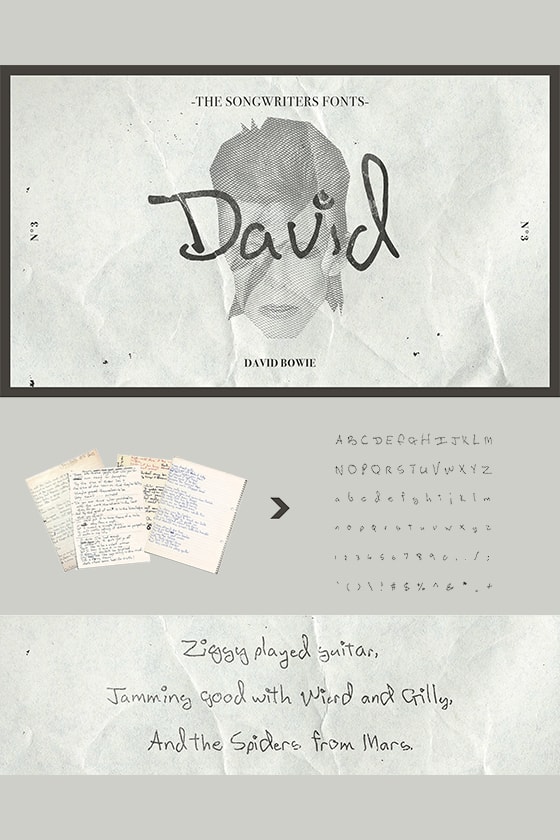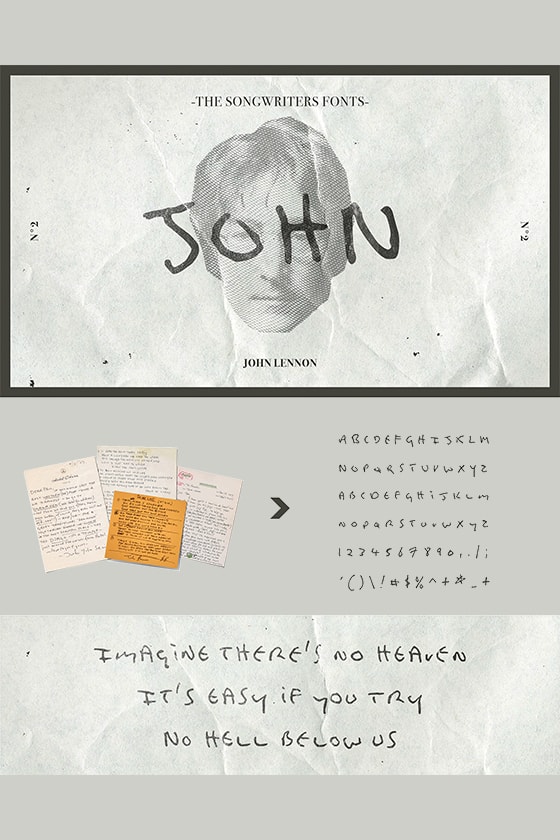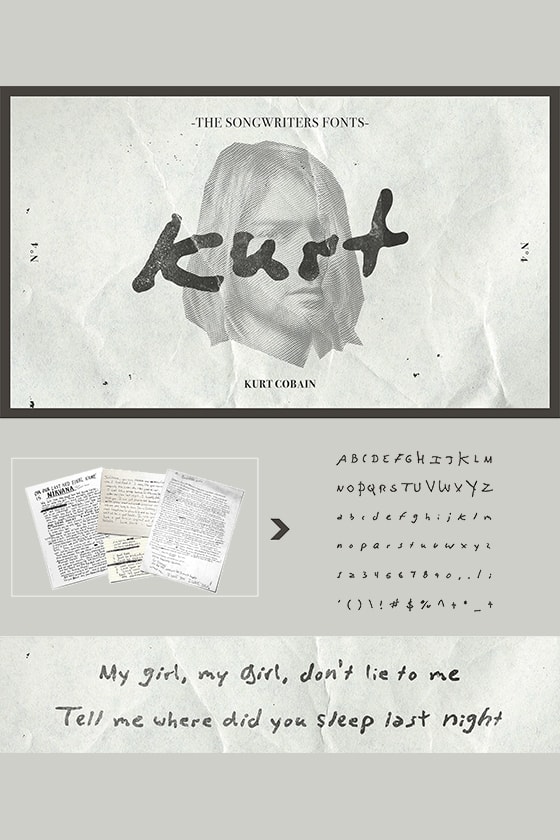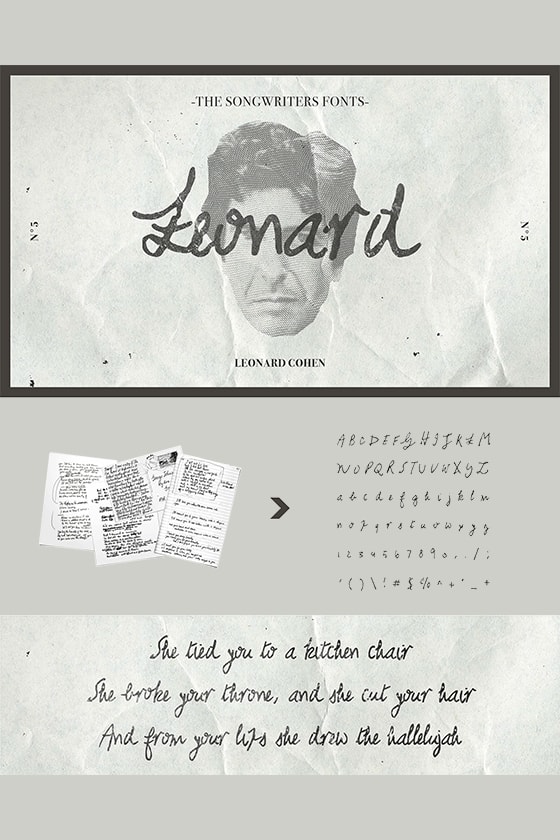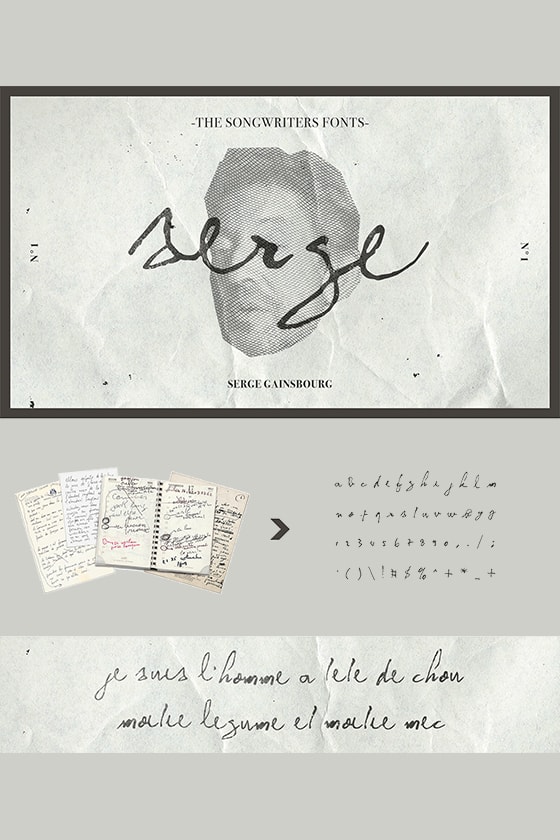
把 David Bowie、John Lennon 的墨寶據為己有…快下載這 5 位傳奇音樂人的手寫字體吧!
很多人說手寫字可以反映出人的性格,但現代人打字多過寫字,現在能找到帶著溫感的文字已經很難,那有想過你有機會以傳奇音樂人的文字去為你表達自己的情感嗎?兩位字型設計師 Nicolas Damiens 和 Julien Sens 把 5 位已逝世的傳奇音樂巨星的手寫字變成數碼字體「Songwriters Fonts」,免費給人們下載,讓樂迷能再次與這些傳奇人物連結,重溫昔日的光景。
這系列「Songwriters Fonts」的字型有David Bowie、John Lennon、Leonard Cohen、 Kurt Cobain 和 Serge Gainsbourg 五位傳奇音樂人的手寫筆跡,設計師把他們的信件和筆記作基礎,整理出屬於他們各人的一套手寫字體。
透過字跡可以讓我們看到一個人的內在,都信這 5 位音樂人的獨特個性也能於他們的字跡上反映出來,例如 John Lennon 雖然是搖滾樂手,但他寫的字卻非常工整,帶著秀氣;而 David Bowie 的字比較接近圓形,隨性卻整齊,像他多變的個性;Leonard Cohen 的字就偏向潦草,像他的作品一樣,帶著詩人和文學氣息。他們的字就像音樂一樣,對不同人都有著吸引力,那你最喜歡的是哪個音樂人的字體呢?